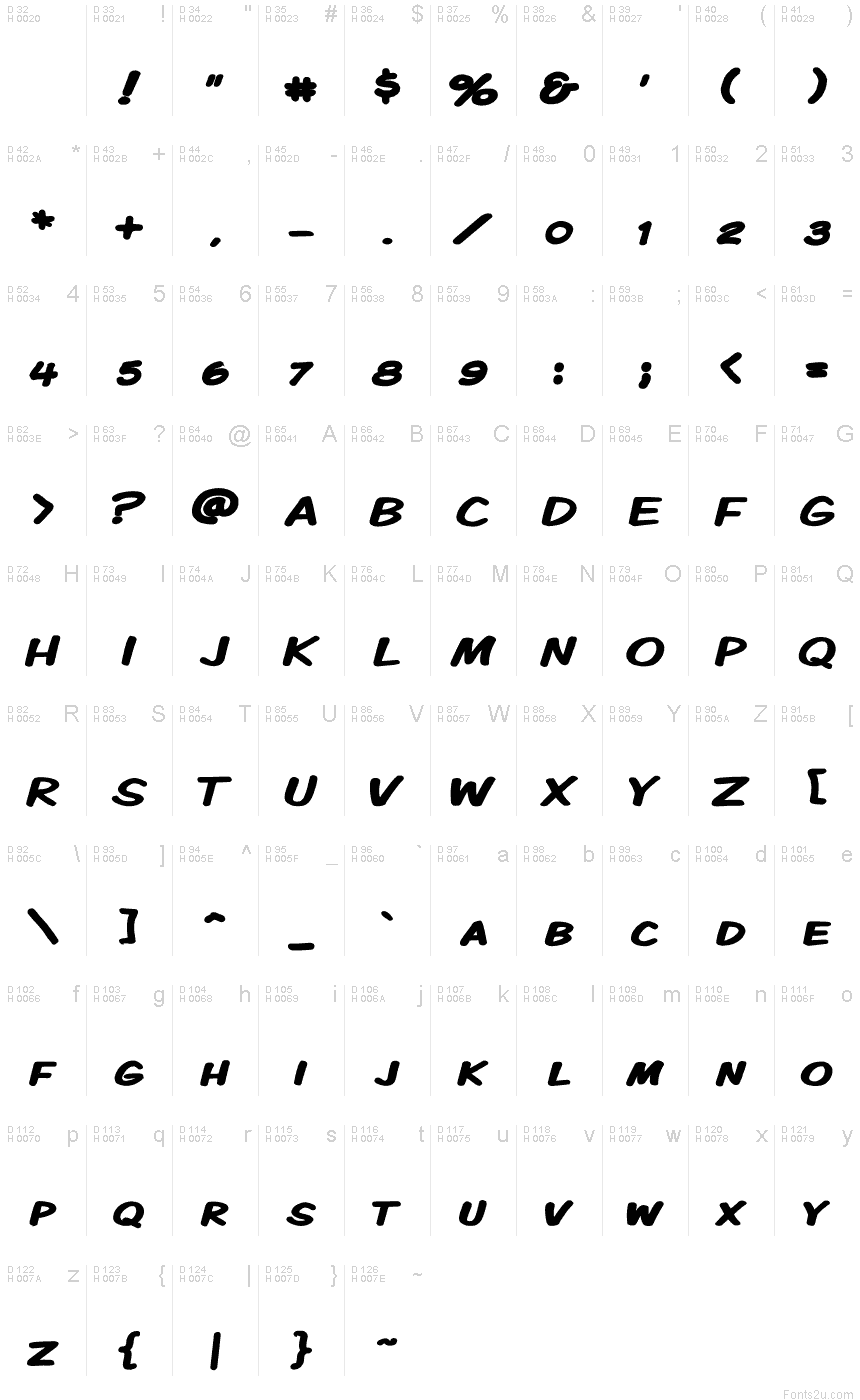
Komika Display Kaps Wide Bold od WolfBainX & Apostrophic Labs to darmowy, komiksowy krój pisma o wyrazistych, masywnych literach, które wyglądają jak wyjęte prosto z ręcznie rysowanego dymku. Szerokie proporcje, nachylone kreski i lekko drżące, atramentowe krawędzie nadają każdemu słowu pełną energii prezencję, nie tracąc przy tym na czytelności. Litery ściśle przylegają do siebie, tworząc solidne, mocne bloki tekstu, które natychmiast przyciągają wzrok.
Wykorzystaj Komika Display Kaps Wide Bold w panelach komiksowych, tytułach książek dla dzieci, zabawnych plakatach, miniaturach na YouTube, naklejkach czy interfejsach gier. Ten darmowy font najlepiej sprawdza się w dużym rozmiarze i pogrubieniu, idealnie pasując do krótkich fraz, które mają brzmieć jak efekt dźwiękowy. Prosta wskazówka: użyj czystego, neutralnego bezszeryfowego kroju do tekstu głównego, a Komika niech gra pierwsze skrzypce w nagłówkach i wyróżnieniach.